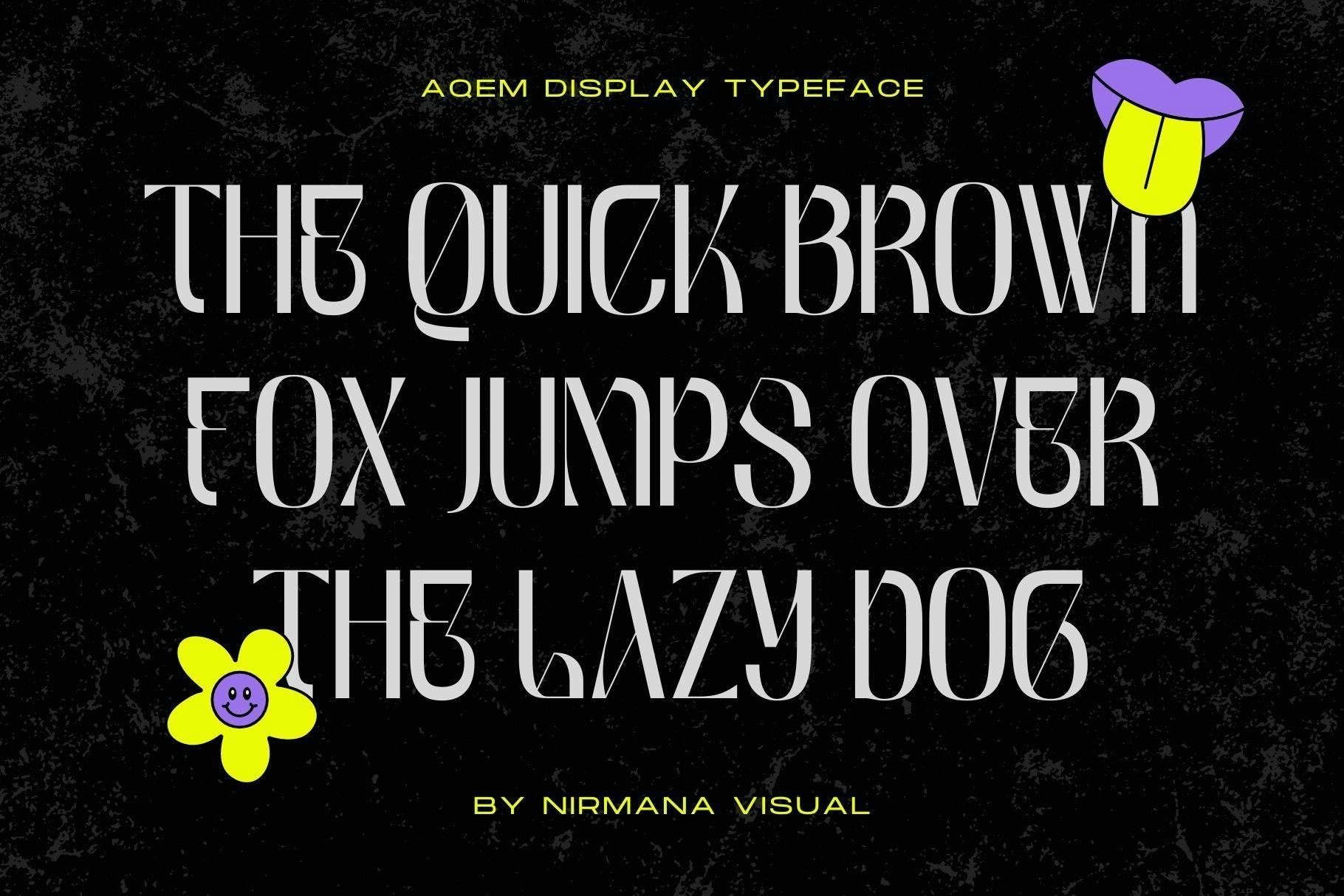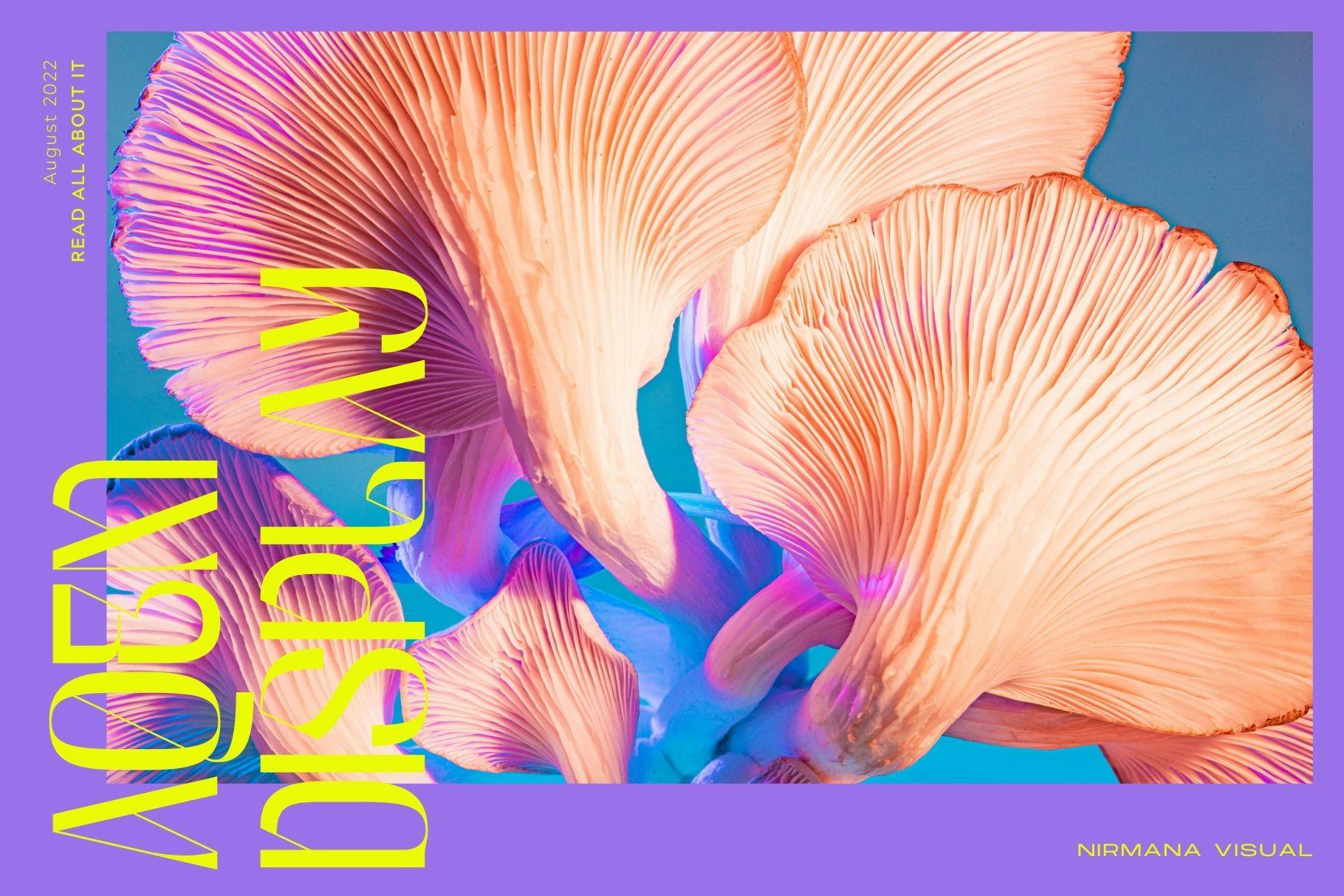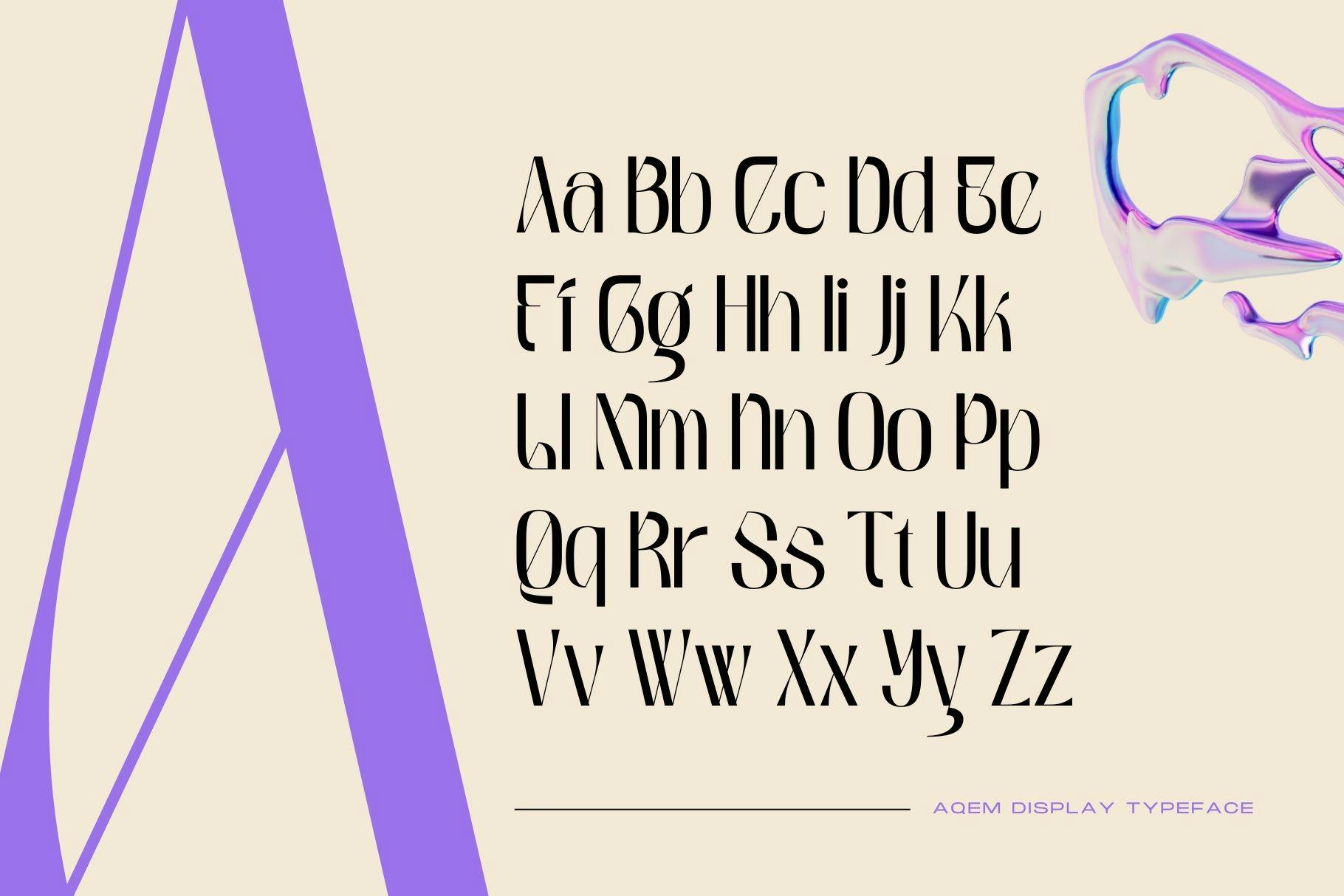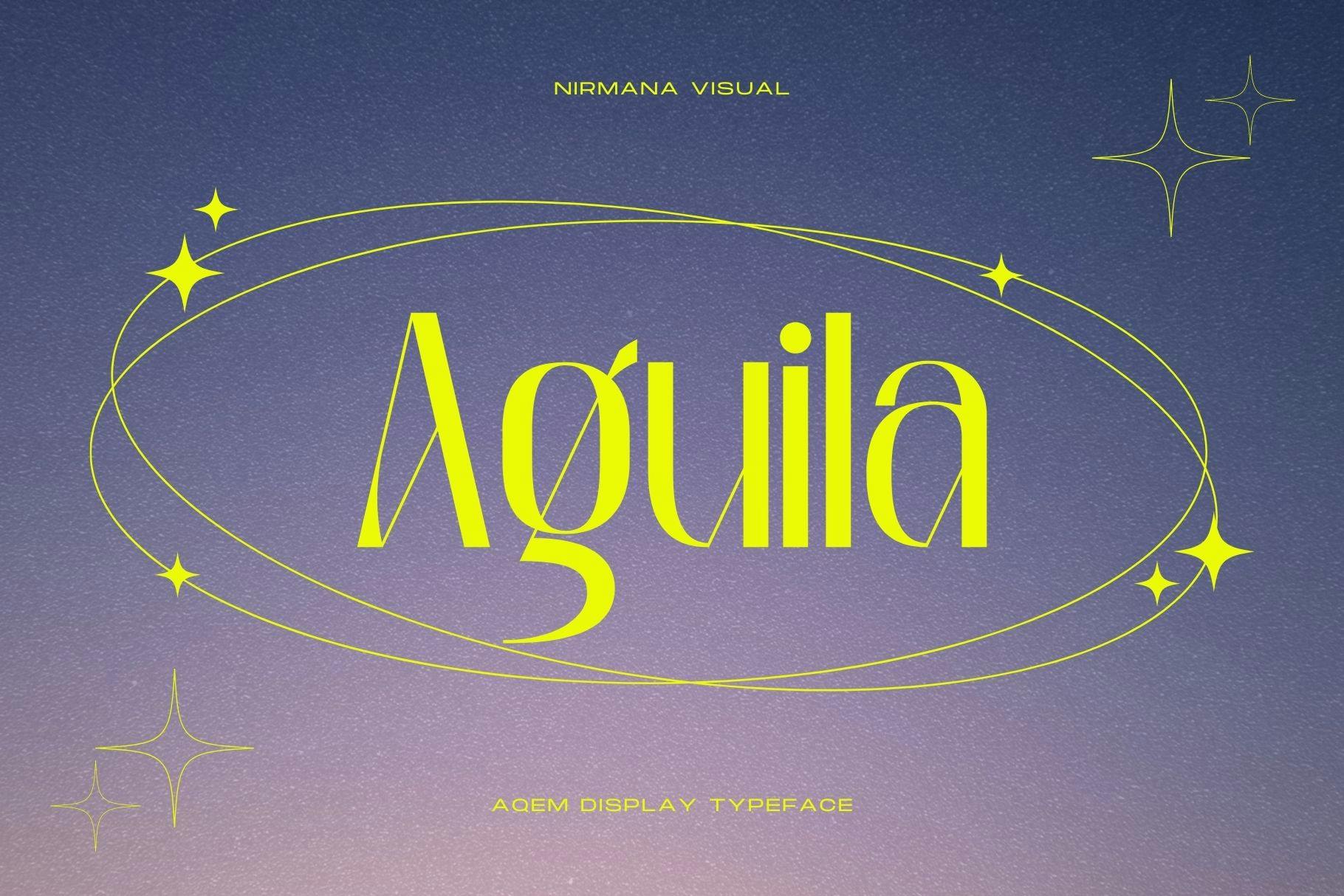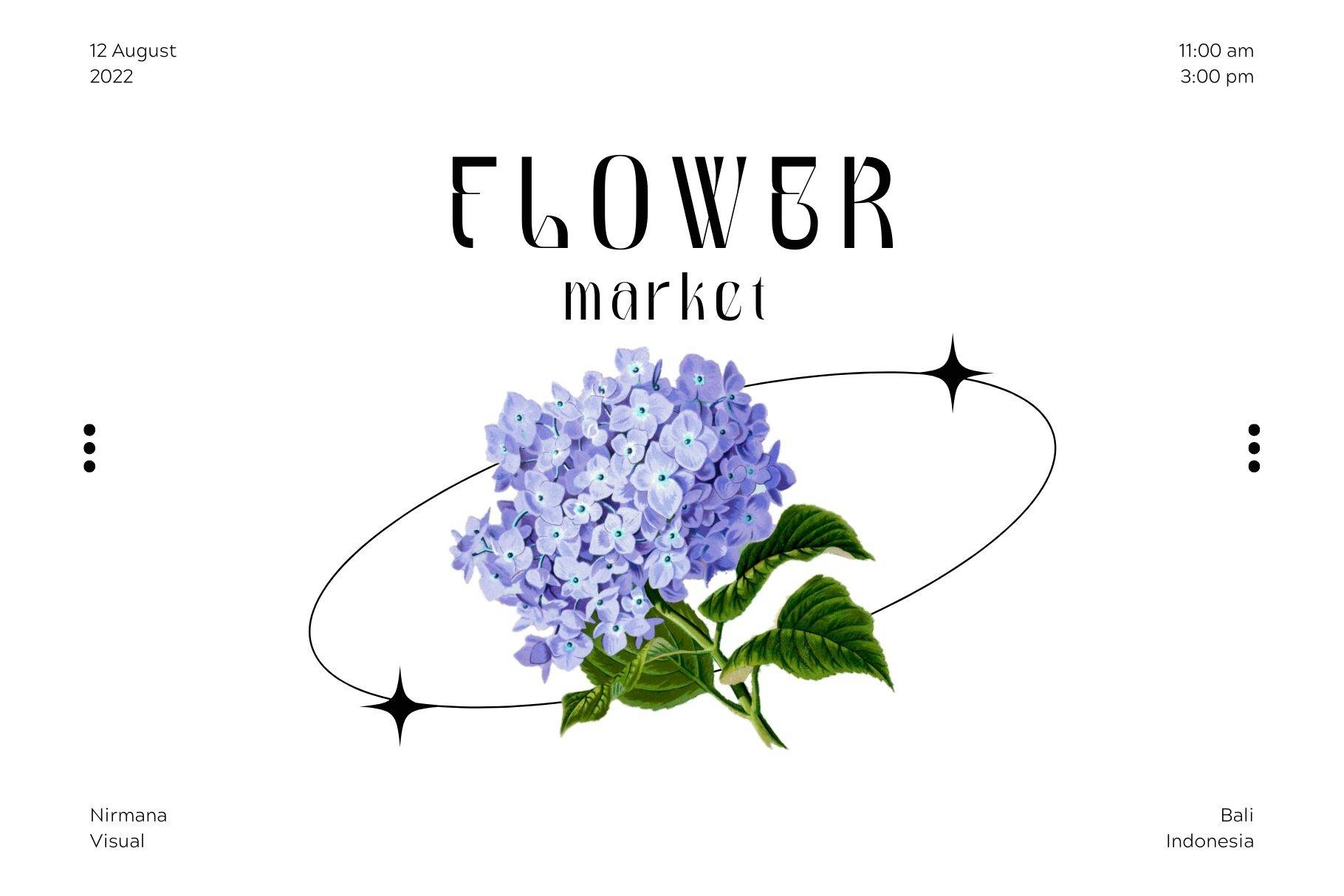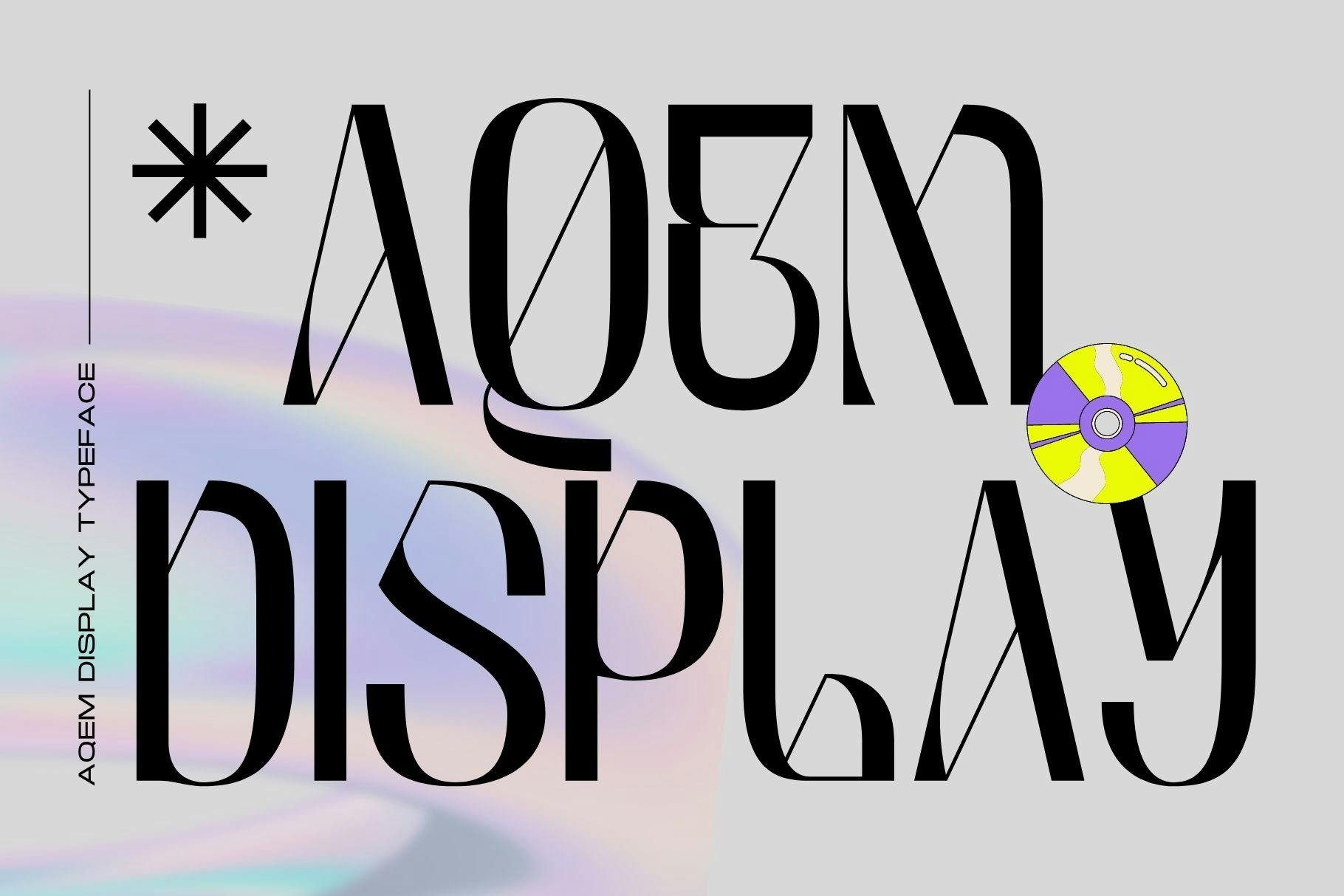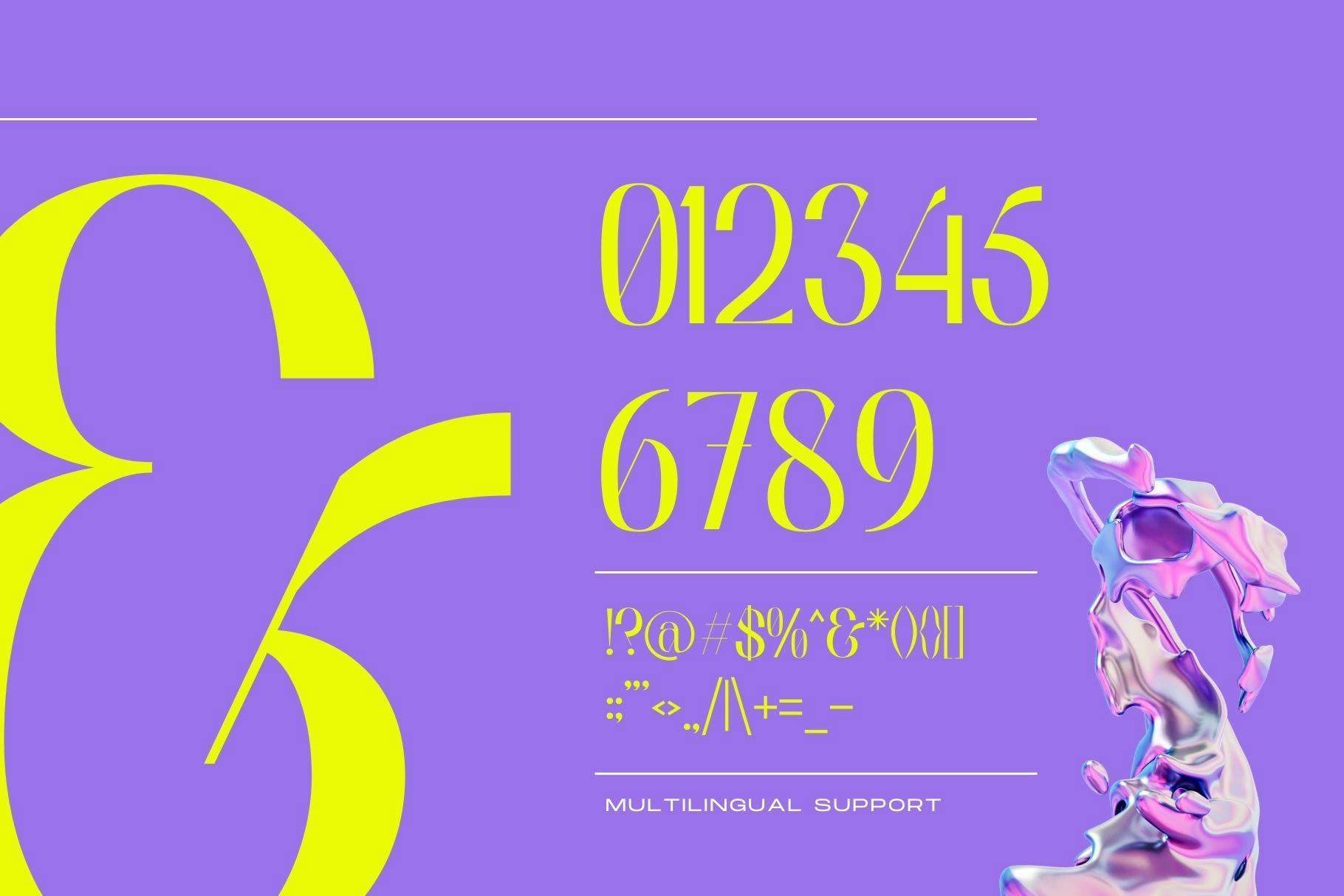
Aqem Logo Font
فونت لوگو Aqem با الهام از طراحی نوآورانه، مناسب برای پروژه‌های مختلف طراحی.
Aqem با الهام از دوره طراحی آرت نوو، زیبایی و هارمونی تایپوگرافیک را در پروژه‌های طراحی متنوع، از جمله لوگو و برندینگ، پست‌های شبکه‌های اجتماعی، تبلیغات و طراحی محصولات ارائه می‌دهد.